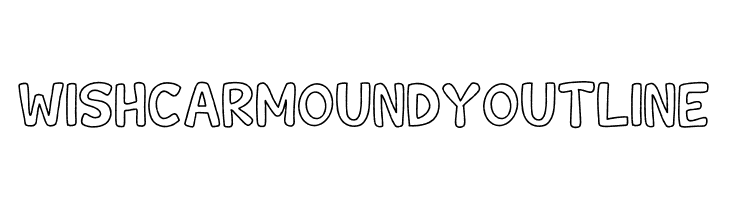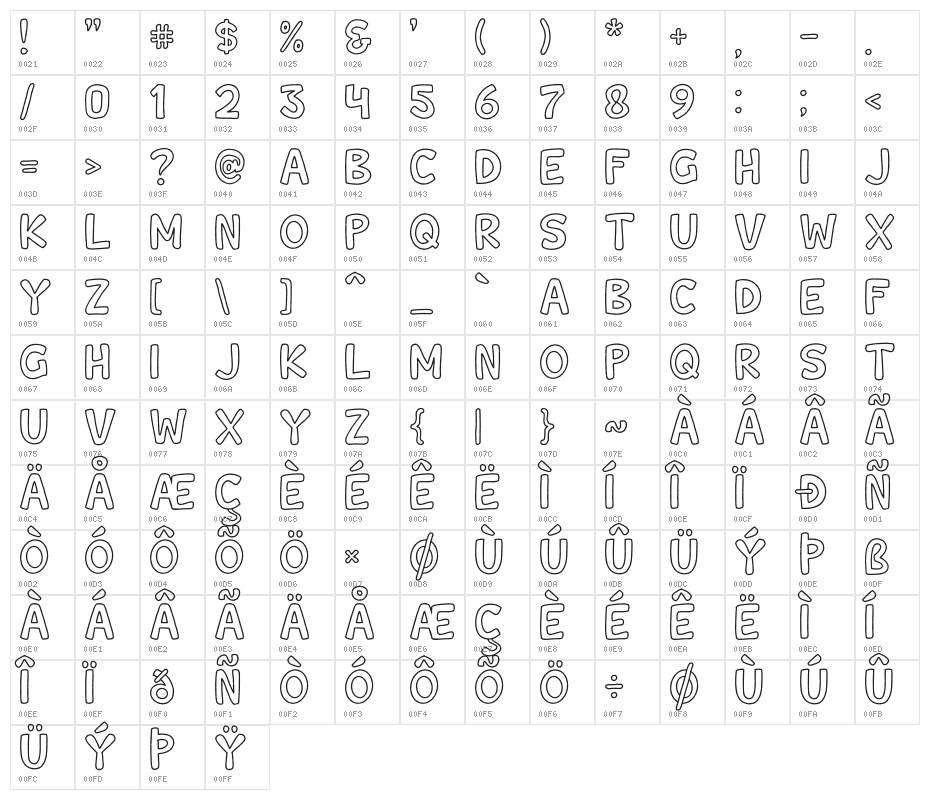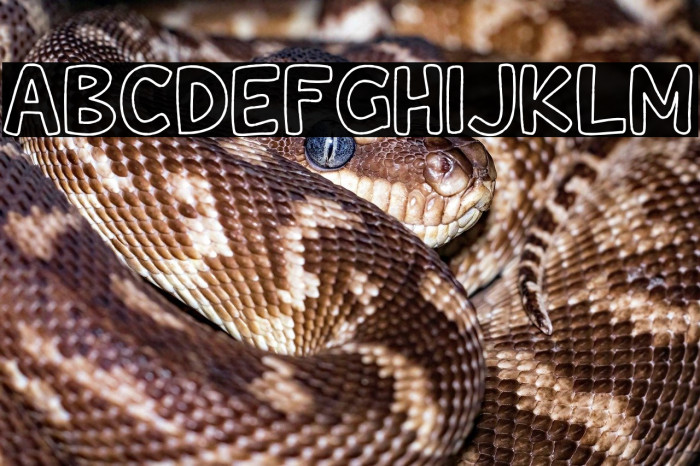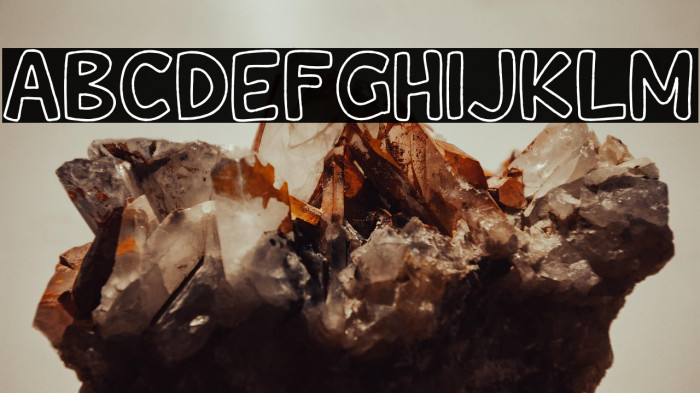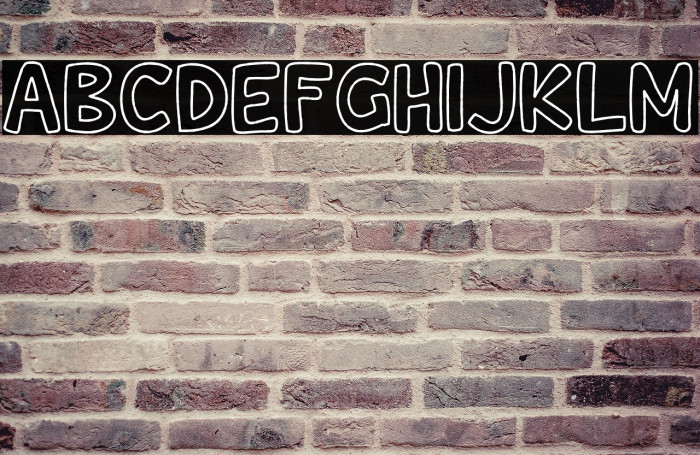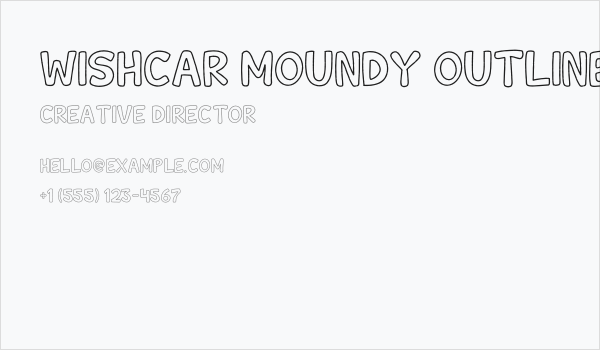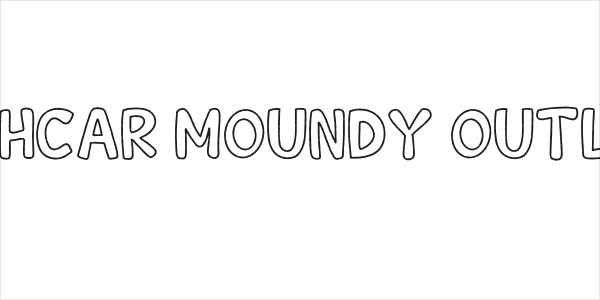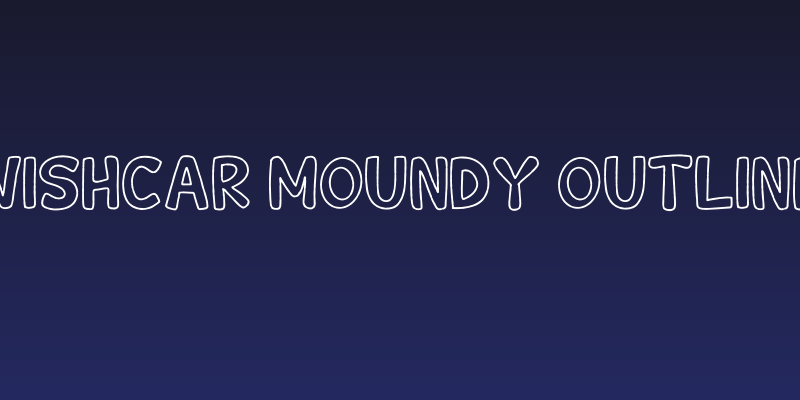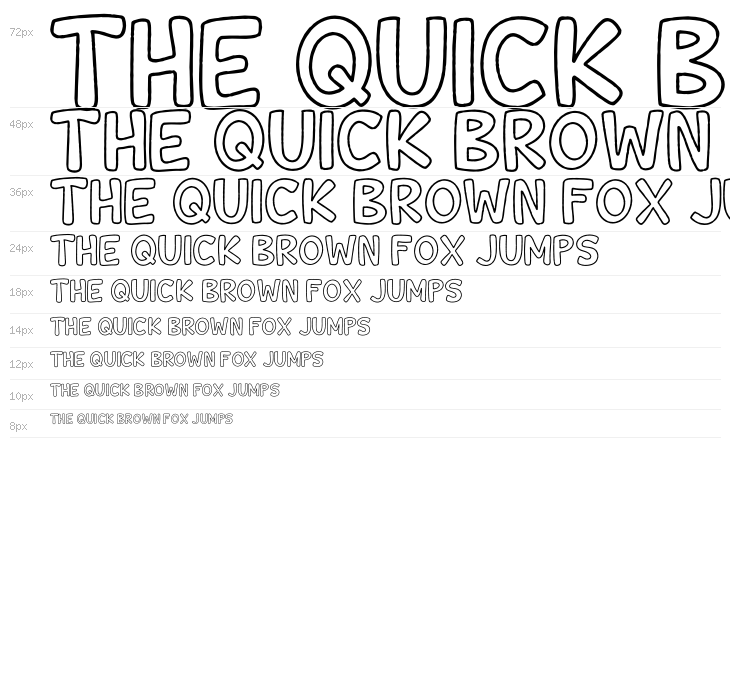
Wishcar Moundy Outline Font
| 全体的なスタイル | Playful, Whimsical |
| おすすめプロジェクト | Ideal for children's books, party invitations, playful branding, and casual posters. |